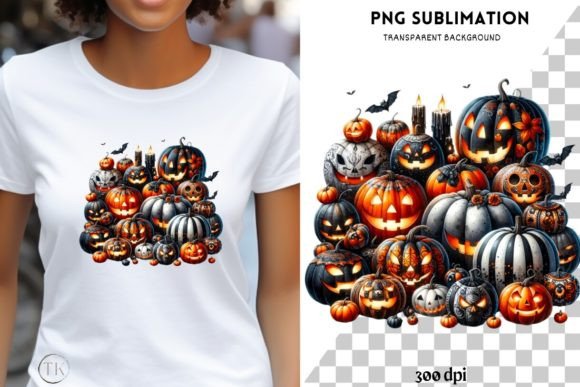
Pumpkin Patch Digital Crafting
Пошук відповідних елементів дизайну може бути складним, але Pumpkin Patch Digital Crafting пропонує виняткову колекцію, яка миттєво покращить вашу роботу.
Створений з високою точністю, Pumpkin Patch Digital Crafting забезпечує чисті вектори, плавну типографіку та комерційну ліцензію для вашого спокою.
Незалежно від того, чи створюєте ви продукти POD (друк на вимогу), весільні запрошення або графіку для соціальних мереж, Pumpkin Patch Digital Crafting стане ідеальним вибором.